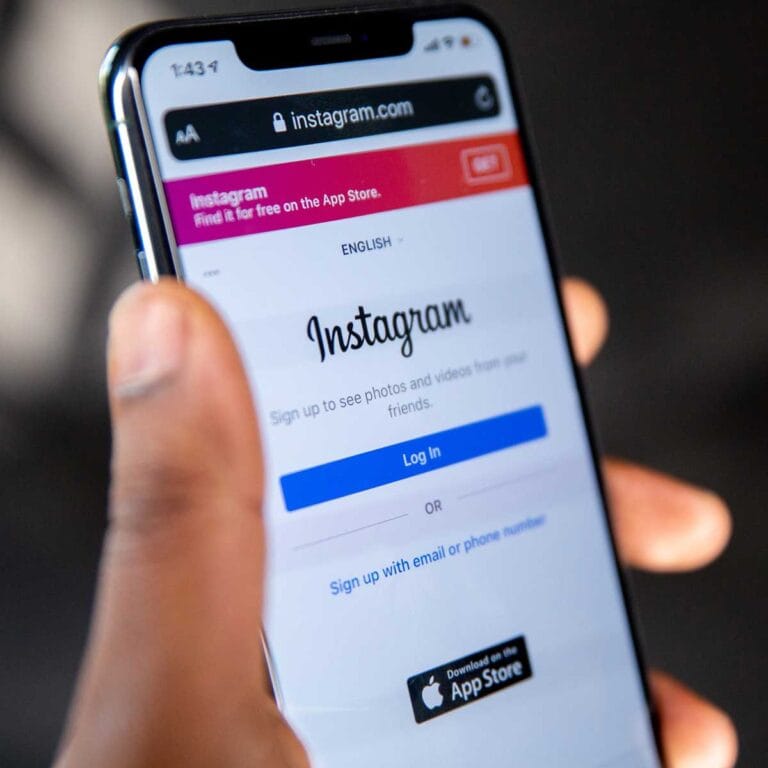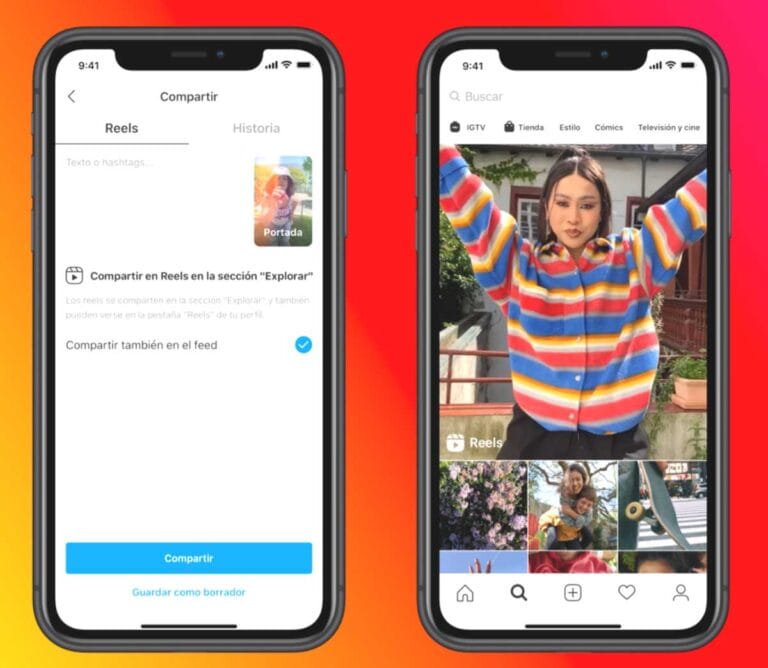
¿Quieres conocer las mejores tipografías para Instagram? Sigue leyendo este artículo y descubrirás muchos detalles para aprender como destacar usando las distintas tipografías.
Cuando se trata de la marca visual, hay algunos detalles comúnmente olvidados o malentendidos. Verás, hay una diferencia entre el diseño convencional, y el diseño particular para las plataformas de medios sociales, no sólo por el tamaño sino también por el orden y la forma de los elementos en una composición.
Por ejemplo, en el caso de la fotografía para redes sociales, podemos experimentar con diferentes ángulos en busca del movimiento adecuado. Para un vídeo, podemos hacer muchas locuras porque se aprecia en estos canales. Pero cuando se trata de un aspecto general, como las fuentes utilizadas, podemos ver grandes errores por ahí. Por cierto, recuerda siempre que debes usar videos propios o de bancos de videos gratuitos, aunque modifiques o añadas diferentes tipografías.
¿Cuáles son las tipografías por defecto en Instagram?
A menos que hayas hecho un cambio en tu biografía de Instagram, ésta aparecerá con la fuente predeterminada de Instagram, Neue Helvetica. Este tipo de letra se utiliza para la mayoría del texto dentro de la aplicación, como los pies de foto y los comentarios.
Sin embargo, si eres un usuario de Android, verás tu biografía en Systems Roboto en lugar de Neue Helvetica. Los titulares y otras líneas de texto más grandes están en la fuente Freight Sans.
La única función que te permite cambiar el tipo de letra dentro de la propia aplicación de Instagram es Stories. Allí, puedes elegir entre estas nueve fuentes:
- Classic
- Modern
- Neon
- Typewriter
- Strong
- Drop-Shadow
- Comic Sans
- Serif
- Sans Serif
¿Por qué deberías personalizar tus tipografías en Instagram?
Una de las principales razones por las que querrás cambiar la fuente de tu historia de Instagram es para ayudar a aumentar las posibilidades de que tus seguidores compartan tu contenido.
El contenido que se ve bien se comparte, y cuando tus seguidores comparten tu contenido, es probable que consigas nuevos seguidores, y si estás usando Instagram para promover tu negocio, entonces eso también aumenta las posibilidades de que esos nuevos seguidores se conviertan en clientes.
Aunque no te importe demasiado el aspecto de una fuente, vale la pena que te tomes un momento para jugar con diferentes efectos para mantener las cosas interesantes.
Errores comunes que se cometen
Es normal que un tipo de letra incluido en una composición visual para medios sociales pueda parecer torpe, fuera de tamaño o incluso sin algo en común con el espíritu de la marca. Por lo tanto, la gente podría perder el interés en los posts porque no parecen naturales, o más bien, porque no parecen estéticos. Incluso si tus fuentes son bonitas, si no aplicas la correcta, podría estropear todo tu trabajo.
Además, hay otro error común sobre las fuentes. A veces, tienes el par adecuado, pero sólo son buenas individualmente, o quizás quieres combinar ocho tipos diferentes. Si entiendes que menos es más, podemos decirte que una mezcla de cinco tipos de letra diferentes no es adecuada para los mensajes de las redes sociales. En cambio, dos o tres serían una mejor opción.
Conseguir la combinación correcta de fuentes es otro tema delicado, y se necesita tiempo y práctica para conseguir la correcta. Por eso, primero te invitamos a que eches un vistazo a estas magníficas opciones de fuentes.
¿Cuáles son las mejores tipografías para Instagram?
No podemos decirte en realidad cuáles son las mejores tipografías para Instagram, ya que eso dependerá del estilo y la personalidad de cada persona o empresa, pero a continuación te dejamos una lista de algunas tipografías para Instagram muy interesantes y que añadirán cierta variedad para tus Stories y trabajos de diseño gráfico.
1. Anton
Anton es otra topografía para Instagram muy popular de Google Fonts que puedes utilizar en tus banners de redes sociales. Si eres activo en Pinterest, Anton puede ser un gran apoyo, ya que es una fuente en negrita con buena legibilidad, lo que la hace adecuada para el tráfico de Pinterest que viene a través de los teléfonos móviles.
2. Abel
El aspecto comprimido y erguido de la tipografía Abel podría hacerla parecer inicialmente aburrida o monótona. Sin embargo, su capacidad para captar la atención no falla en comparación con otro tipo de tipografías.
Al parecerse a una fuente tipográfica, se puede utilizar para revelar el título de películas o clips a modo de máquina de escribir y funciona bien en todos los tamaños y temas.
3. Dancing Script
Los blogueros de viajes o los fotógrafos de las redes sociales han recurrido a nuevas formas de mostrar su trabajo en estos medios. Una de las más comunes es la de encapsular sus fotos en un fondo blanco liso con una leyenda debajo.
Dancing Script es lo que se puede utilizar para acentuar tus fotos con texto
4. Rock Salt
Escribir en polaroids es una de las cosas más milenarias que se exhiben en Instagram. Si deseas adquirir ese aspecto digitalmente, asegúrate de echar un vistazo a la fuente Rock Salt.
Compuesta por letras manuscritas, ligeramente desgastadas, pero perfectamente legibles, puedes utilizarlas en tus fotografías para que parezcan tan auténticas como una polaroid.
5. Poiret One
Elegante, sencilla y artística: estas son las características de Poiret One. Un tipo de letra curvada pero muy legible, que ofrece muchas posibilidades.
Utilizada principalmente para textos cortos, esta fuente es muy geométrica y se compone en gran medida de curvas y líneas rectas. Puede utilizarse para etiquetas de correos, rótulos y titulares de carteles.
6. Neuton
Neuton es un tipo de letra uniforme y formal que puede utilizarse para contenidos diversificados, y que es compatible con múltiples navegadores.
Es compacta y perfecta para párrafos largos o elementos visuales con mucho texto.
7. Nawabiat
La tipografía para Instagram Nawabiat es muy popular, y no es de extrañar, su look exótico y diferente hace que destaque entre las demás fuentes.
Es especialmente utilizada para publicaciones de frases.
Descarga la tipografía Nawabiat aquí
8. Tikal Sans
Con 6 variaciones en su haber, esta fuente polifacética puede utilizarse en todos los tamaños y tiene usos variados debido a sus diversas formas.
Tikal Sans en su forma ligera es perfecta para subtítulos en vídeos; y los titulares en su carácter envalentonado.
Puedes descargar la fuente Tikal Sans en este enlace
9. Novecento
Esta fuente extravagante, fuerte y naturalmente audaz puede ser de gran ayuda si quieres atraer la atención hacia tu publicación.
Si eres uno de esos blogueros que aspiran a tener un elaborado banner o una cuadrícula de imágenes en sus perfiles de Instagram, esta fuente puede ser muy útil.
Cuando alguien se limita a navegar por tu perfil y no mira cada publicación en detalle, Novecento es la opción más adecuada.
Descarga la tipografía Novecento aquí
10. Montserrat
Una de las fuentes clásicas y atemporales, con la que siempre acertarás, que ayuda a destacar tus publicaciones es Montserrat. Es una de las mejores tipografías para Instagram que peudes utilizar ¡Nunca pasa de moda!
Es profesional, funcional y muy versátil, por lo que puede ir con todo tipo de contenido. Es perfecta para la publicidad de una marca, ya que realza el esteticismo formal.
Es una mezcla perfecta de Serif y Sans serif, que le ofrece lo mejor de ambos mundos.
Consigue la tipografía Montserrat aquí
11. Helvetica
Esta familia tipográfica alberga 7 formas variadas de la fuente, que van desde la ligera, la cursiva ligera, la regular, la cursiva regular hasta la negrita y la cursiva negrita. Básicamente, cada forma tiene dos opciones.
Aunque no es del todo propicia para los logotipos, la excelencia de la Helvética puede utilizarse en cualquier tamaño o forma para todo tipo de leyendas o titulares de gran tamaño.
12. Playfair Display
Cincelada con gracia y elegancia, esta fuente es la preferida en todos los medios y para diversos usos, debido a su versatilidad.
Los blogueros y autónomos del sector del marketing de contenidos alaban esta fuente, pero eso no significa que no pueda utilizarse para carteles o vídeos con poco contenido textual.
Descarga Playfair Display desde Google Fonts
13. Stalemate
Cursiva con pinceladas fuertes Stalemate es una fuente decorativa que no compromete la legibilidad.
Con unas impresionantes 12 opciones, esta fuente puede hacer que los rótulos parezcan extremadamente ornamentados, al tiempo que conservan su gloria y propósito sencillos. Con un toque vintage, se utiliza mucho para los titulares.
Descarga la fuente Stalemate aquí
14. Della Raspira
Si su vídeo contiene texto que desaparece y reaparece, ésta es la fuente que debe elegir. Puede utilizarse para anuncios en las redes sociales. Este estilo de fuente tiene un toque gótico como los tipos de letras góticas.
15. Gabriela
Con un toque femenino y un atractivo rústico, su letra cursiva con elaboradas terminaciones de cada alfabeto, la convierten en una tipografía distintiva y única. Gabriela es una de las mejores tipografías para Instagram cuando deseas publicar con un estilo cute.
Muy utilizado por las marcas de moda y joyería, puede ser un complemento perfecto tus publicaciones de moda en las redes sociales.
Descargar la tipografía Gabriela
16. Ramaraja
Esta tipografía es muy natural y atractiva y puede utilizarse para todo tipo de trabajos, desde logotipos hasta publicaciones en redes sociales
Si quieres una fuente sencilla, legible y que capte la atención, Ramaraja es muy buena opción.
Descarga aquí el estilo de fuente Ramaraja
17. Zeyada
La tipografía Zeyada simula la letra manuscrita, por lo que es usada especialmente para publicaciones de tipo frases, consejos, etc
18. Autour One
Con un atractivo medieval y étnico que brota de su estructura, Autour One está formado explícitamente con alfabetos curvos, que son amplios y reflejan la antigüedad.
Al ser una opción predominante en las portadas de libros populares o en los carteles, puede servir de contraste con su diseño moderno o complementar el de la vieja escuela.
19. CalliGraffiti
Esta es la respuesta a lo que ocurriría si la caligrafía se encontrara con el grafiti. Compuesta principalmente por líneas dentadas pero con trazos más finos y elegancia regia, es una fuente indiscutiblemente única que merece más atención.
Puede utilizarse para los créditos o las menciones especiales de un vídeo o para revelar un mensaje empático a un ser querido.
Descargar Calligraffiti en Google Fonts
20. Nunito
Hoy en día, casi todo el mundo accede a redes sociales en dispositivos móviles, por lo que resulta fundamental que las letras que utilicemos sean legibles y además capten la atención.
Nunito es muy popular porque cumple con ambos requisitos.
21. Amatic SC
Esta fuente, que funciona mejor en mayúsculas, es delgada y sus líneas delicadas y dentadas inducen un atractivo informal y divertido.
Puede utilizarse para hacer anuncios y publicaciones informales.
Puedes conseguir la tipografía Amatic SC aquí
22. Merriweather
Merriweather es un tipo de letra clásico que se utiliza para frases, títulos, pies de fotos, etc.
23. Open Sans
Open Sans es una de las tipografías más utilizadas tanto en publicaciones para Instagram, Facebook, Pinterest y otros tipos de trabajos gráficos, el motivo es su sencillez y su atractivo.
24. Stay Writer
Es una letra de estilo artístico, muy utilizada en post de moda, frases, consejos y espiritualidad. Si quieres algo distinto a lo habitual, a la para que atractivo, Stay Writer es tu tipografía.
25. Junge
Un estilo de letra delgada y sencilla, que puede ser útil para combinar con otros tipos de tipografías y jugar con los contrastes. Una de las mejores tipografías para Instagram.